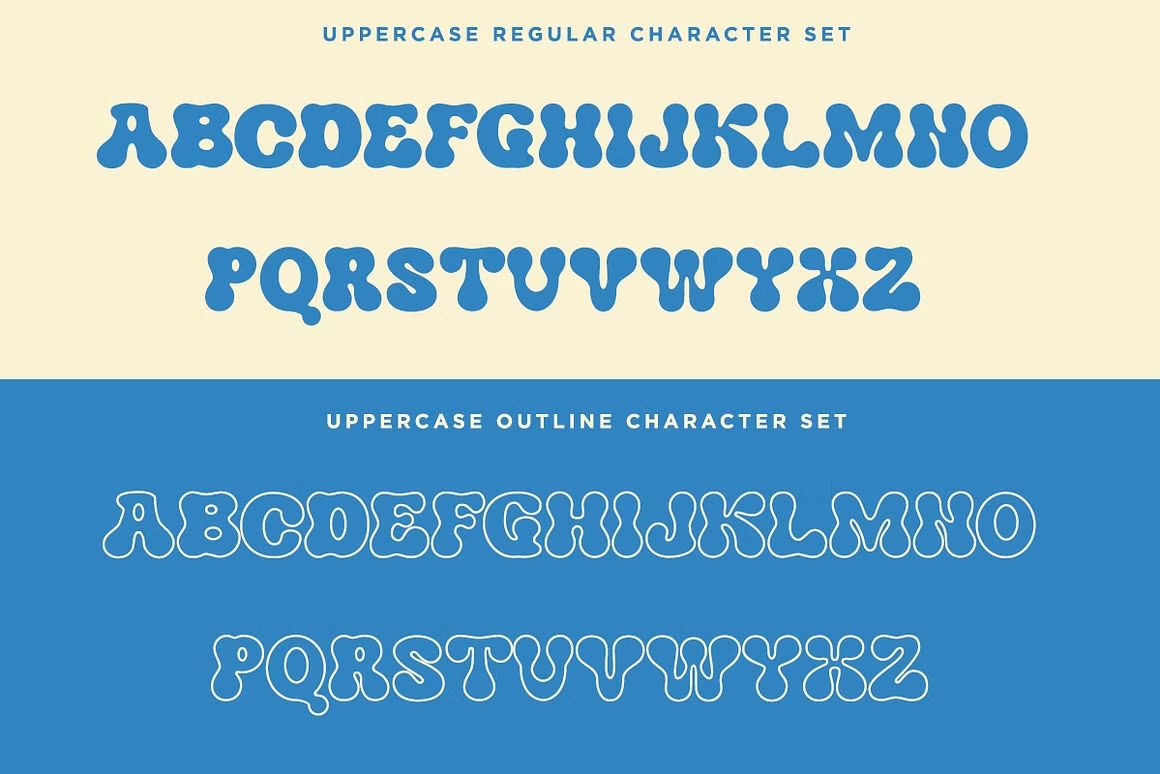
Kringe – Sans Serif Font
Kringe adalah font sans serif tebal dan modern, cocok untuk headline, logo, dan desain yang standout. Format OTF/TTF/WOFF, siap digunakan.
Kringe adalah font sans serif modern dengan desain tebal, tegas, dan berkarakter kuat. Dirancang untuk tampilan yang mencolok namun tetap minimalis, Kringe sangat cocok digunakan untuk headline, poster, logo, branding kreatif, dan kemasan produk. Kombinasi antara bentuk geometris dan garis bersih menjadikan Kringe pilihan ideal untuk desain yang ingin tampil bold dan profesional.
• Sans serif bold dengan gaya modern dan tegas
• Ideal untuk headline, branding, dan desain mencolok
• Termasuk huruf kapital, kecil, angka, dan simbol